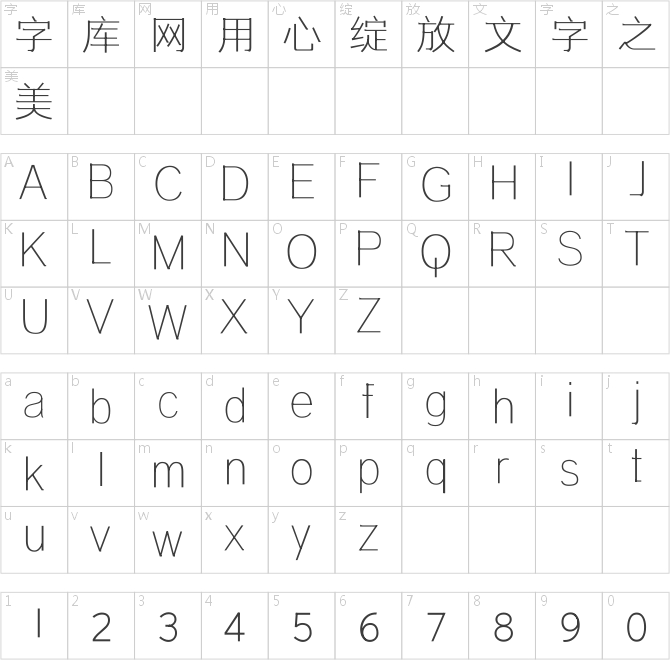
字體名稱: 三極新雅宋黑簡
三極新雅宋黑簡體
三極新雅宋黑簡體介紹
三極新雅宋黑簡體是一款精致活力的字體,豎的起筆和橫的收筆分別類似宋體的起筆和收筆,纖細的筆畫設計增加了字形的易讀效果,精致工整,字體整體筆形纖細,空間布白勻稱。適用于書刊的標題和商業類品牌的廣告語設計、商業產品的包裝設計。
三極新雅宋黑簡體字體SJxinyaSH字庫是一款讓人賞心悅目、百看不厭的中文字體,適合各類廣告和產品包裝設計應用,字體大小2.06MB,格式為ttf字體,上傳用戶是三極字庫,作者/版權方為三極字庫/歐偉